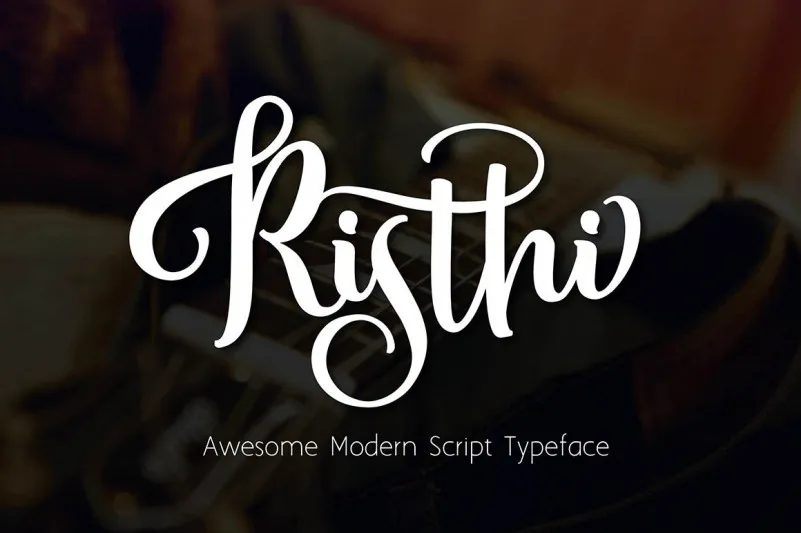
Risthi Script Font – Fonte Grátis
Risthi Script Font
A Risthi Script Font é uma elegante escolha para qualquer projeto gráfico que deseje adicionar um toque sofisticado à sua identidade visual. Desenhada pela Rabbittype e inspirada nos traços finos do filigree, essa fonte de calligrafia apresenta uma mistura perfeita entre o estilo tradicional das folhas de cobra e a modernidade contemporânea. Suas linhas reticentes se movem com leveza e graça ao longo da linha base, criando um contraste encantador que combina elementos elegantes com uma leve exuberância. Com Risthi Script Font, designers podem explorar uma variedade de aplicações, desde gráficos de cabeçalhos e assinaturas até cartões de casamento, camisetas personalizadas, etiquetas, cartazes de notícias ou selos para agradáveis brindes. Seja em qualquer formato de comunicação visual, essa fonte oferece uma versatilidade que certamente ajudará a destacar seu design e torná-lo único. Com suas linhas finas e movimentos fluidos, Risthi Script Font não apenas se assemelha à calligrafia filigree, mas também traz um toque de elegância moderna para qualquer projeto. Se você está procurando por uma fonte que possa dar ao seu design o caráter necessário para capturar a atenção e expressar o seu estilo único, Risthi Script Font é definitivamente uma opção irresistível.